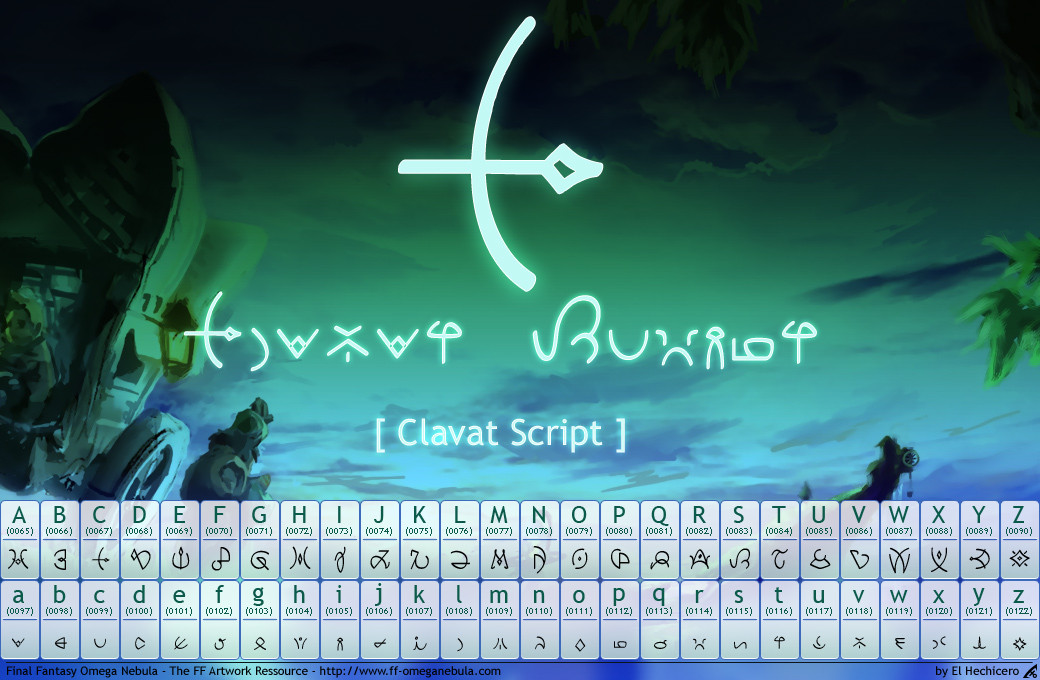
Police d'écriture utilisée dans Final Fantasy Crystal Chronicles---------
Font used in Final Fantasy Crystal Chronicles
Difficile à déchiffrer, mais très jolie écriture..!!